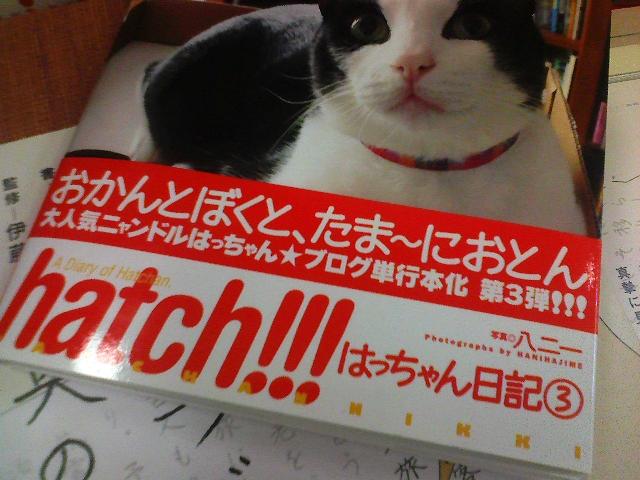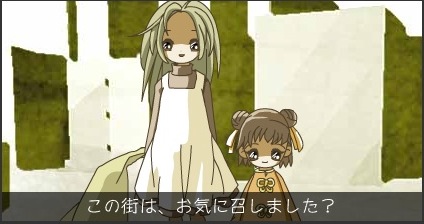
よしのやのよし  よし  2007年12月23日(日) 0:44
はじめまして。
購入を検討しております。
セプテンバーによしのやの「吉」(土・口)はあるのでしょうか?
さとうゆたか  2007年12月23日(日) 9:23 [修正]
こんにちは よしさん。
セプテンバー頒布ページに記したように、JIS X 0208-1990全字種(第一水準漢字2965字、第二水準漢字3390字、非漢字524字)以外の漢字は含んでおりません。
残念ですが『よしのやの「吉」(土・口)』はJIS X 0208に入っていないのです。
ハッピーマナーブック  さとうゆたか  2007年12月2日(日) 21:07
このサイトのフォント、大きな文字はほとんどセプテンバーが使われています。
雑誌の体験広告記事  さとうゆたか  2007年12月1日(土) 13:33
ナイキとアップルがコラボして生まれた、新しいグッズ&サービス「Nike+」。
4ページにわたる広告記事のほとんどに使われています。
夕暮れ自転車  さとうゆたか  2007年11月26日(月) 20:34
「くりすてねっと」で公開されているサウンドムービー「夕暮れ自転車」の字幕書体に採用されております。
ゆっくりと楽しんでください。
ガリ版のような懐かしい書体  ちょく  2007年11月1日(木) 8:12
はじめまして
子供達とノート交換をしています。
大人っぽい文字は、威圧感とか、隔たりを作るのではないかと思っています。かといってワープロ文字を貼り付けるのも味気ないです。
そこでガリ版文字を思い出し、フォント探しをはじました。そこでセプテンバーに出会いました。ネーミングもいいですね。書体とマッチして、竹内まりあやアースウィンドアンドファイァが頭に浮かびます。
中学生時代にガリ版新聞を作っていました。歳がバレますが、教頭先生に文字の書き方を教わりながらガリ版にさからわず書くのがコツだと教わりました。
パソコンでも活用し、手書きでも真似したい書体です。
ところで、L、M、等幅の違いがよくわからないので、教えていただけますか。
「L」とか「M」は、太さです  さとうゆたか  2007年11月1日(木) 9:41 [修正]
ちょくさん こんにちは 投稿ありがとうございます。
洋服などのサイズ表示と違って、フォント名についている「L」とか「M」という文字は、そのフォントの太さをあらわしています。
Lは、Lightの略で、軽い・細い…という意味です。
Mは、Mediumの略で、中間・普通…という感じかな。
セプテンバーの頒布ページの一番上にあるサンプル画像にも、いちおう見本があります。
Lをダウンロード購入しました  ちょく  2007年11月2日(金) 11:43 [修正]
見本をダウンロードして、まず自分の名前を打ってみました。
教科書で使われない文字が名前に含まれているのか、全部でませんでした。
思い切ってLを購入しました。
自分の名前がセプテンバーで表示されました。
気に入りました。今度から自署するときはこの書体にしようと思いました。
今まで、点や短い線で書いていた部分を長めにはっきりと書くとか、横棒のながさとか、書いた本人が見て気持ちいいので、見た人の感想を聞きたいところです。
パソコン画面で表示するにはLではぼやけるし、小さめに表示されますが、これは設定でしょうか。
サンプルのMはやはりしっかりと見えます。
Lにボールドをかけるのも品がないので、Mも欲しくなりました。
Re:Lにボールドをかけるのも品がない  さとうゆたか  2007年11月2日(金) 12:32 [修正]
ご購入ありがとうございます。
パソコンで見る場合「L」は、ちょっと細く感じるかもしれません。
サイズを大きくすれば大丈夫ですけどね(でも、そういうわけにもいきませんよね)。
ちょくさんは、Macをお使いのようですね。システム環境設定のアピアランス→滑らかな文字の設定で、調節してみてください。
わたしは弱にしています。
「ボールドをかけるのも品がない」たしかにその通りです(目が肥えていらっしゃる)。
みんな安易にボールド指定したりしますが、美しい結果は得られません…。
必要な太さでデザインされたフォントを使うべきだと思います。
本のタイトル  交茶店  2007年9月8日(土) 18:04  HP Mail
神保町の店頭でセプテンバーM(だろう)の
書体使用の本を発見。
映画にもなったらしい、
重いタイトルではあります。
書体で目にとまりましたが、
格安になっていたこと(笑)
100ページ余りそれとタイトルで購入です。
2003年12月20日初版
さとうゆたか  2007年9月8日(土) 19:02 [修正]
投稿ありがとう。この本、購入したんですね〜。
わたしの場合、書店で少し他人目を気にしながら撮影しています。
著者名とか出版社を掲載しますから、誰にも迷惑はかからないだろうとの思い込みで…。
本の書名に  さとうゆたか  2007年8月28日(火) 10:36
がばいばあちゃんの勇気がわく50の言葉
作者: 島田 洋七
出版社: 徳間書店
Mをちょっと太らせているようだ。
50の文字、字間がくっつきすぎに感じる。
使って楽しい  JINTA  2007年8月10日(金) 0:31
はじめまして、JINTAと申します。
今日、ラベルライターでファイルの背表紙を作って、貼る仕事に
セプテンバーを使ってみました。
予想以上にキレイにでき、しかも目に優しい!
私も作るのが楽しくなりました。
好きなフォントだと仕事が楽しくなります。
かわいくて見やすいフォントってなかなかありません。
ステキなフォントを作ってくれたタイプラボさんに感謝!!です。
さとうゆたか  2007年8月10日(金) 9:21 [修正]
JINTAさん こんにちは。
この書体を使って仕事が楽しくなった…なんて、ウレシイな。
セプテンバーを使って、仕事や生活をこれからも楽しく彩ってください。
再生少女のテロップ  さとうゆたか  2007年7月11日(水) 20:23
音楽と少女作りの頁「くりすてねっと」で公開されている、サウンドムービー「再生少女」第三話以後のテロップに使われています。
なかなか、いい雰囲気ですね。
通勤電車で  もりた  2007年6月11日(月) 0:24
Lを購入して使っています。フォントを購入したのは初めてでしたが、とても気に入っています。
通勤時に、電車のドア上部に貼ってある広告で使われているフォントがセプテンバーではないかと気づきました。
某携帯の広告で、TVCMでも見ている内容でした。
最初はただ読んだだけだったのですが、毎日同じものを見ているうちに「このフォント、なんか見たことある」と思って、そこに注目してみたら自分も使っているアレだとわかりました。
PC画面で見るとそうでもないですが、印刷すると文字のフチが滑らかになって、なんともあたたかい感じがします。
その広告では犬たちが会話をするフキダシの中で使われていますが、他にもあると思うので探してみようと思っています。
さとうゆたか  2007年6月11日(月) 7:33 [修正]
情報ありがとう!
セプテンバーは細いので、あまり目立たないんですよね。
あちこちに使われているはずなんですけど、
かなり意識していないと、視線が通り過ぎてしまいます。
パソコン画面でも、文字の輪郭を滑らかに表示するように設定すると、
いい感じになりますよ。
文字サイズをちょっと大きめにしないと、効果が出ないかもしれませんが…。